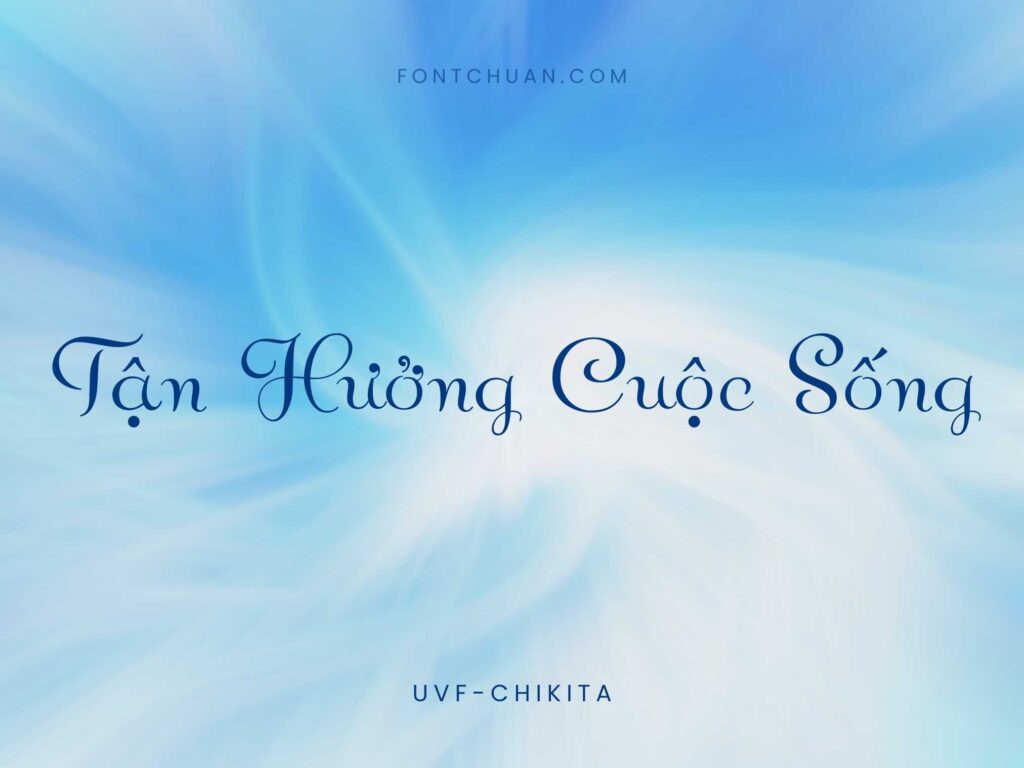
Font UVF Chikita Việt Hóa
UVF Chikita là một font chữ script dễ thương và tinh tế, nổi bật với các đường nét mềm mại, uốn lượn và mang phong cách trẻ trung, vui nhộn. Với kiểu dáng nhẹ nhàng và thanh thoát, font này thường được sử dụng trong các thiết kế sáng tạo như thiệp mời, bao bì sản phẩm, logo hoặc các ấn phẩm trang trí mang tính cá nhân hóa cao. Nhờ nét vui tươi và sinh động, UVF Chikita còn có thể thiết kế như Font sinh nhật để tạo ra các poster, thiệp mừng hoặc banner sinh nhật độc đáo, vừa tươi mới vừa thu hút người xem.
Font này được sưu tầm và đăng bởi thành viên của Font Chuẩn. UVF Chikita hỗ trợ đầy đủ các ký tự tiếng Việt, mang lại trải nghiệm sử dụng hoàn chỉnh cho người dùng. Ngoài ra, font này còn hỗ trợ nhiều ngôn ngữ khác, mở rộng phạm vi ứng dụng trên toàn cầu.